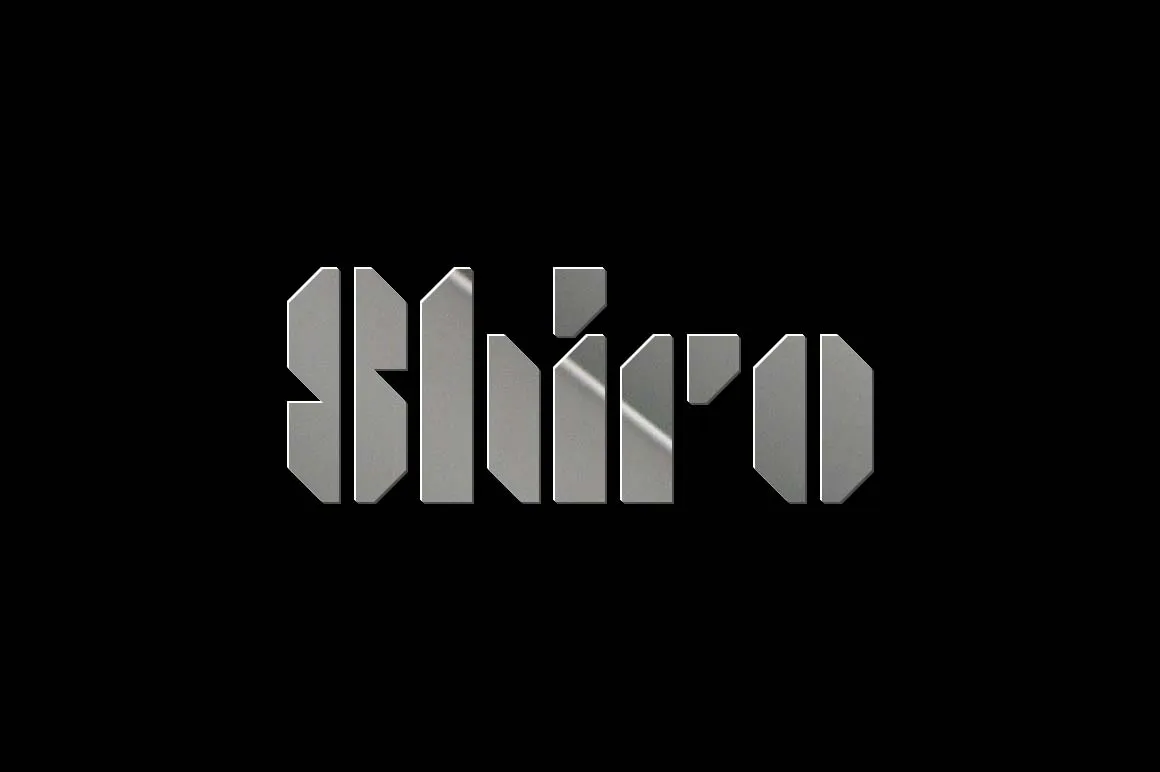
Shiro Font – Download Grátis
A Shiro Font é uma deliciosa novidade para os amantes do pixel art! Esta custom font foi criada pelo designer talentoso Hamilton, apresentando um estilo único e futurista que contrasta perfeitamente com a estética minimalista e neon da era digital. Perfeita para aqueles que adoram reviver o encanto dos anos 80 e 90 em suas criações digitais, esta fonte pixelada oferece cores vibrantes e formas geométricas que certamente vão deixar seu trabalho de design um passo além do usual. Download agora e faça a diferença nos seus projetos, Hamilton’s Shiro Font é uma escolha perfeita para adicionar o toque final ao seu design!